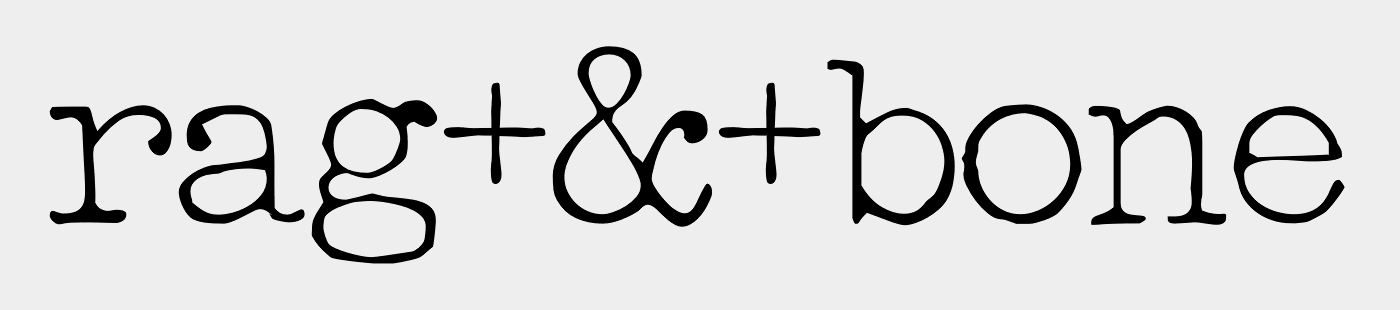
Schriftname gesucht
ich suche den Namen dieser Schrift.
Hat vielleicht jemand einen Tipp für mich?
die Passport ist ähnlich, aber nicht die gesuchte. Die Unterbrechung im &, das n und der waagerechte e-Strich sind deutliche Unterschiede …
Irgendeiner der vielen "Elite"-Fonts könnte es sein.